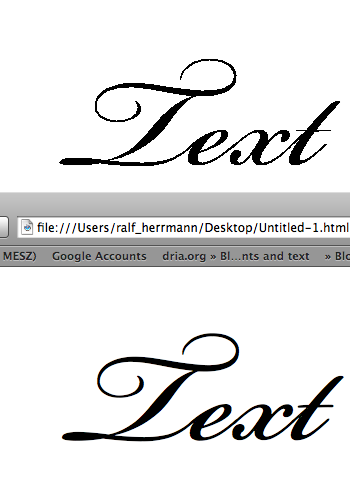
ich weiss garnicht was alle an cleartype finden. ich find das grässlich. :evil:
We read best, what we read most.
Mehr ist es wirklich nicht. Reine Gewohnheit. Solange man nicht an einer alte Röhre sitzt, kann ich jedem Windows-User nur empfehlen, es anzuschalten und dann die 2 Wochen des vermeintlichen Unwohlseins durchzuhalten. Es IST einfach das überlegenere Rendering. Wer sich einmal dran gewöhnt hat, will sicher nicht mehr zurück.
ich sitz am lcd und mags lieber scharf. jedem das seine. bei mir ist es jedenfalls off. außer halt im IE7 aber den nutze ich ja nicht.
im übrigen finde ich es interessant das du dich auf einmal so für font-embedding einsetzt, dachte immer du warst dagegen ... :?:
ich sitz am lcd und mags lieber scharf.
Wenn wir dich in den nächsten Jahren dann mit Webfonts zuballern, wirst du's ja doch irgendwann einschalten müssen. :twisted:
im übrigen finde ich es interessant das du dich auf einmal so für font-embedding einsetzt, dachte immer du warst dagegen ... :?:
Ich hab's ja im Artikel beschrieben:
Doch die Zeiten ändern sich. Mit der heute am PC und Mac üblichen Text-Darstellung über Subpixelrendering ist es heute auch ohne aufwändig programmierte Bildschirmoptimierung möglich, beliebige Fonts in guter Qualität darzustellen.
Ich sitze hier vor Safari und schaue mir die Graublau Sans Web an, die besser dargestellt wird, als es MS mit manuellem Delta-Hinting je hinbekommen hätte. Warum sollte ich das nicht anerkennen?
Wenn ich früher gegen Webeinbettung argumentiert habe, dann auf Basis der damaligen Darstellungsqualität. Auf Basis von Subpixelrendering habe ich nichts mehr dagegen. Und für mich als halber Webdesign und halber Typedesigner ist die Verbindung der beiden Welten natürlich verständlicherweise hochspannend. :)
naja, schon allein wegen dem "zuballern" werde ich es ausschalten.
so hatte ich auch immer deine kritik verstanden, find dein zitat leider
nicht mehr (vielleicht gabs das auch nicht und ich habe dich falsch
verstanden) dachte immer du hast etwas gegen den einsatz von
font-embedding weil die "seiteneinsteiger" somit noch mehr zum
herumspielen haben. aber du hast recht, die gutgestalteten webseiten
und die lesbarkeit wird sich durchsetzten, wobei ... wieviel leser hat
die bild-zeitung? ;) ok, hoffen wir das beste.
Also haben wir mindestens 3 Szenarien, die Safari Bildschirmglättung, die Windows-ohne (voreingestellte) Bildschirmglättung und die Vista (mit voreingestellter) Cleartype-Glättung.
Wie ich jetzt erst feststelle, ist es unter Windows sogar noch verzwickter:
Setzte ich eine Webseite eine Zeile mit einem TrueType-Font und habe ClearType an, bekommen ich ClearType-Rendering. Soweit klar.
Aber: Kommt eine PostScript-basierte OpenType-Schrift zum Einsatz, wird das ClearType-Rendering ausgeschaltet und normale Graustufen-Kantenglättung benutzt. :shock:
Aber es kommt noch schlimmer: Aber einer bestimmte Schriftgröße wird selbst das abgeschaltet und der OpenType-Font wird ohne jegliche Kantenglättung dargestellt. :cry:
Und dies kommt auch direkt vom System, passiert also in IE7, Firefox 3 und jedem Browser, der diese Render-Engine benutzt.
Hier ein Beispiel:
Bild 9.png[/attachment:1psnk82v]
Unten hervorragendes Subpixelrendering in Safari, oben in IE7 mit eigentlich aktiviertem(!) ClearType. :oops:
vielelicht kann man sie mal wieder aufnehmen. was gibt es neues und wie weit ist die technik und deren verbreitung heute?
und dann hab ich noch mal eine frage zu dm angedachten artikel zum thema mit einer übersicht? gibt es den bereits oder kommt der noch?
(Edit, ca. 1 Stunde später. Siehe unten)
Ich hoffe ich mache mich nicht unbeliebt, wenn ich mit meinem ersten Post Leichenfledderei betreibe, aber mir ist etwas aufgefallen und Google hat mir noch kein zufrieden stellendes Ergebnis geliefert.
Über die Unterschiede im Font-Rendering zwischen Systemen und Browsern wurde ja schon viel geschrieben, aber das alles erklärt mir immer noch nicht die etwas fette Darstellung von Fonts in meinem Safari.
Hier ein Screenshot einer Testseite mit einer per @font-face eingebetteten Schrift. Schriftvorschau über „Webinformationen einblenden“ aus dem „Entwickler“-Menü eingeblendet.
bildschirmfoto20110512u.png
Bei genauer Betrachtung ist die Darstellung in der Seite etwas fetter als in der Vorschau.
Links Browserfenster, rechts „Webinformationen“-Vorschau:
bildschirmfoto20110512u.png
Macht Webkit da etwas anderes/zusätzliches als die Systemschriftenglättung?
Wird die Schrift farbig, hell auf dunklem Untergrund und/oder über CSS mit Schatten versehen, tritt der Effekt noch deutlicher auf. Was genau passiert da?
Was genau passiert da?
Das eine ist eine Subpixel-Darstellung, das andere ist Graustufenkantenglättung. Dass die unterschiedlich aussehen, ist normal. Dass die Standardeinstellung manchen zu fett vorkommt, kann gut sein. Ich gehe aber mal davon aus, dass das eben bewusst die Leserlichkeit von kleinen Schriftgraden verbessern soll weil es dem Wegbrechen von dünnen Linien entgegenwirkt. Bei der von Dir im Beispiel gewählten Schrift ist das natürlich weder nötig noch hilfreich.